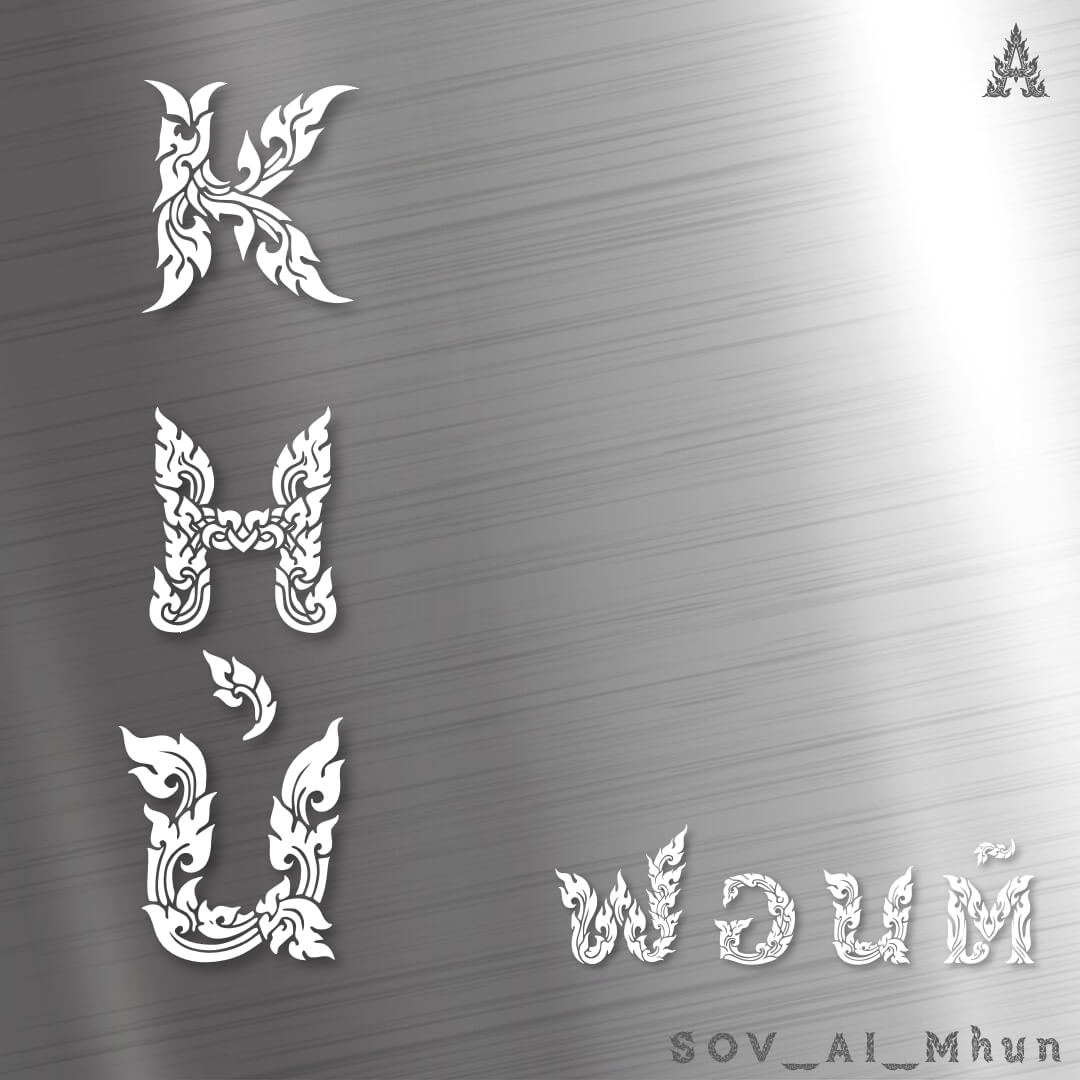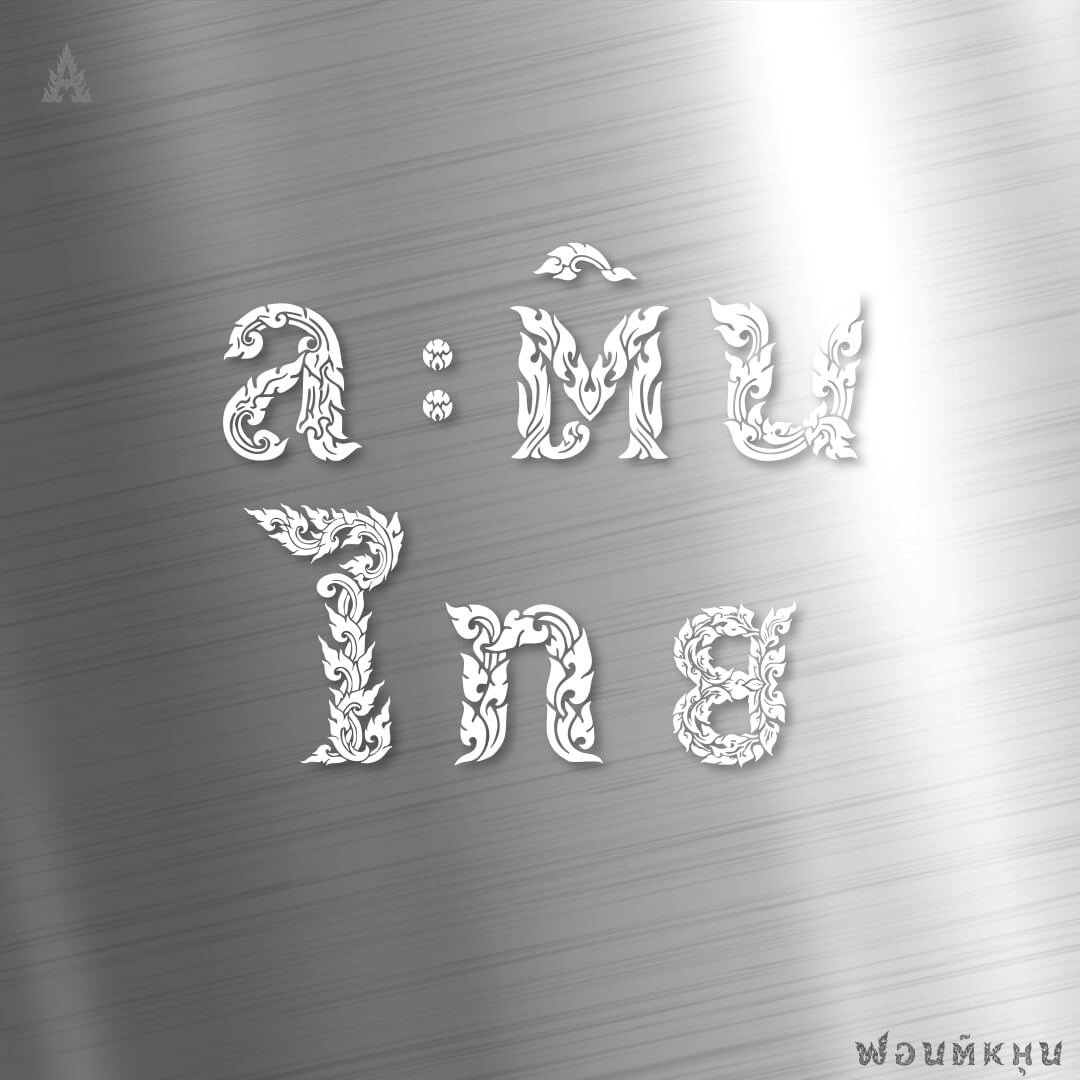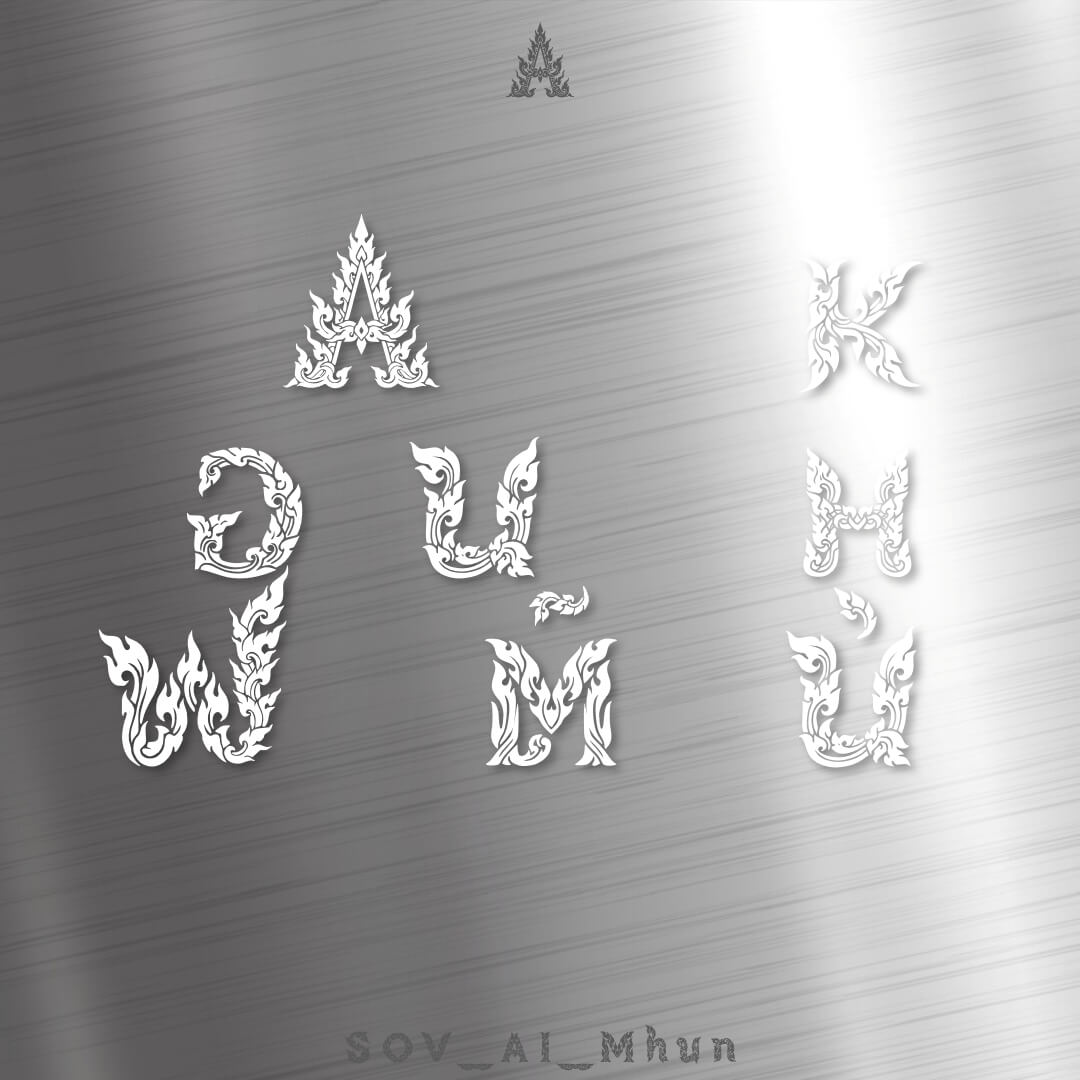
หมุน – เป็นฟอนต์ทดลองนำ AI มาช่วยงานออกแบบที่ซับซ้อน โดยให้ออกแบบลายกนก แล้วขอให้ปรับรูปร่างคล้ายตัวอักษรละติน จากนั้นก็เอามาหมุน พลิก ตะแคง ตัดแปะให้เป็นอักษรไทย
เบื้องหลังการออกแบบ : ฟอนต์ หมุน
หมุน (SOV_AI_Mhun)